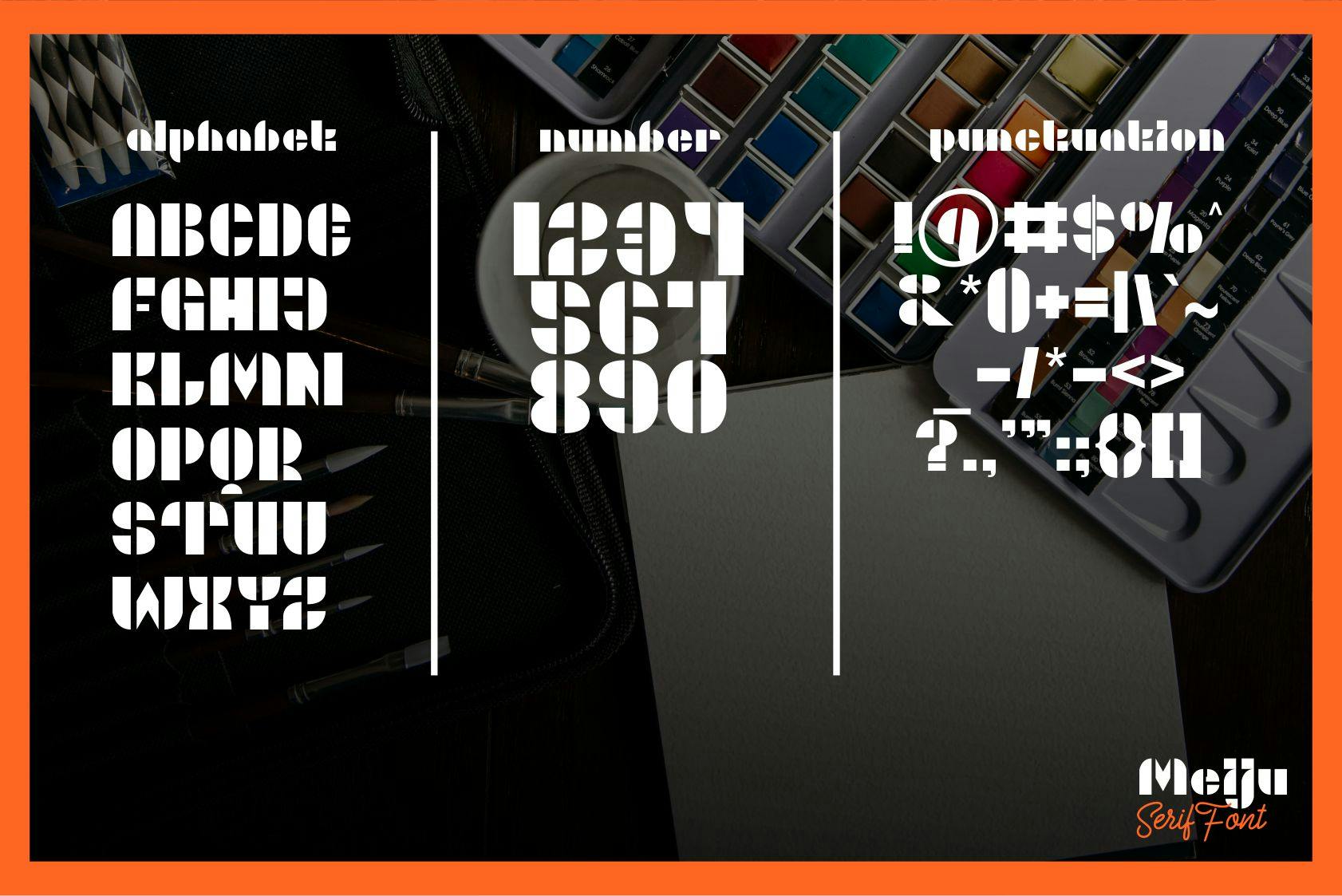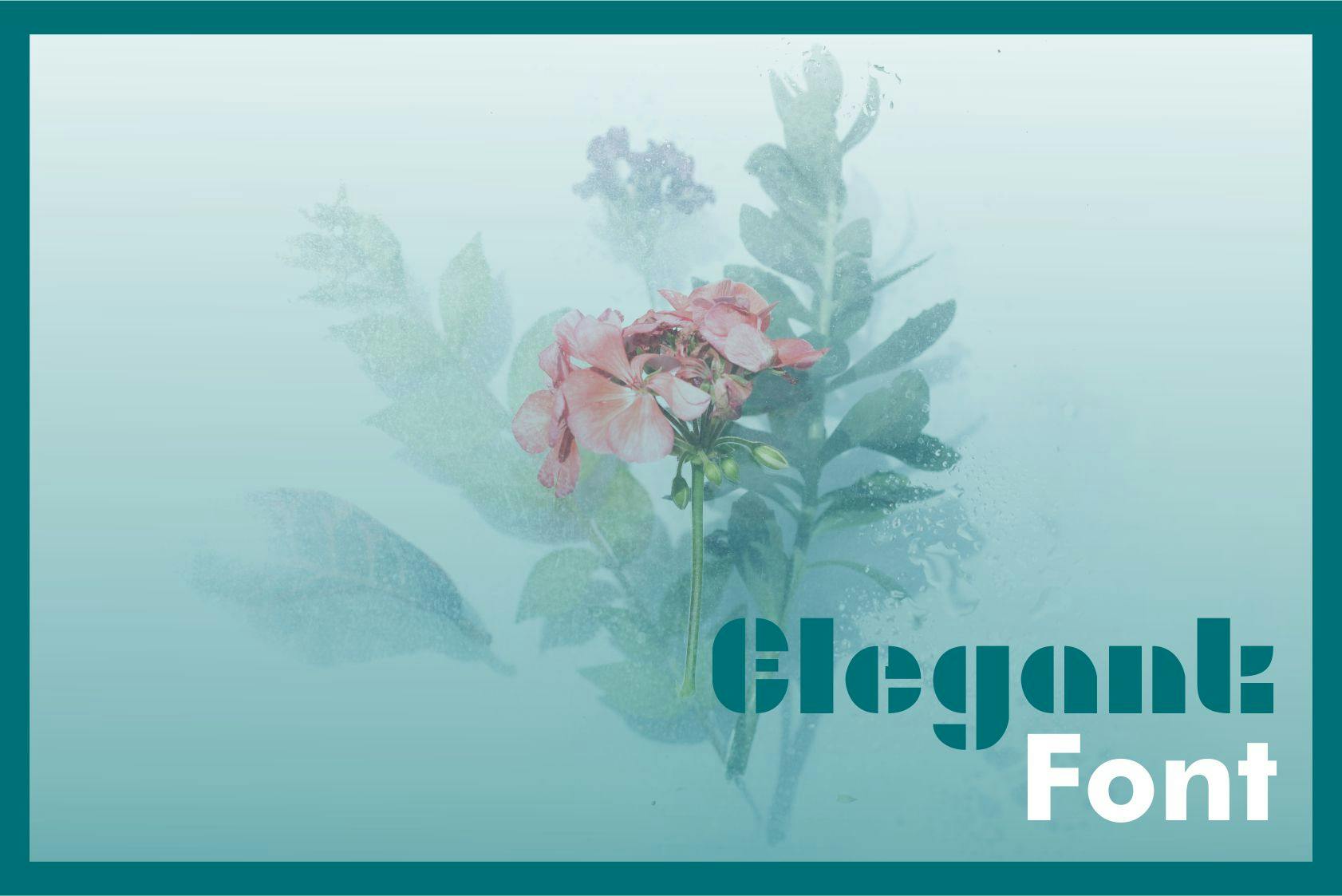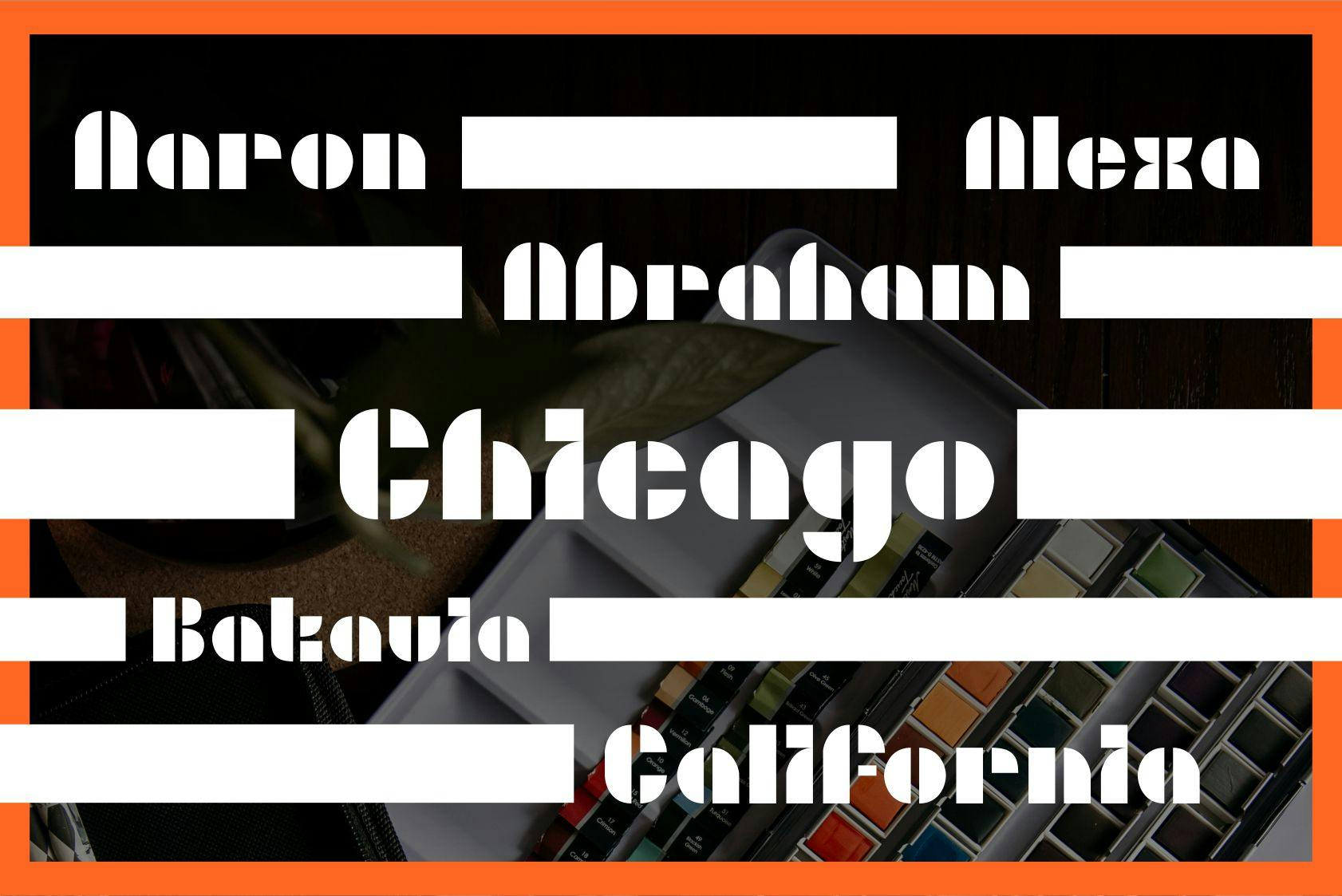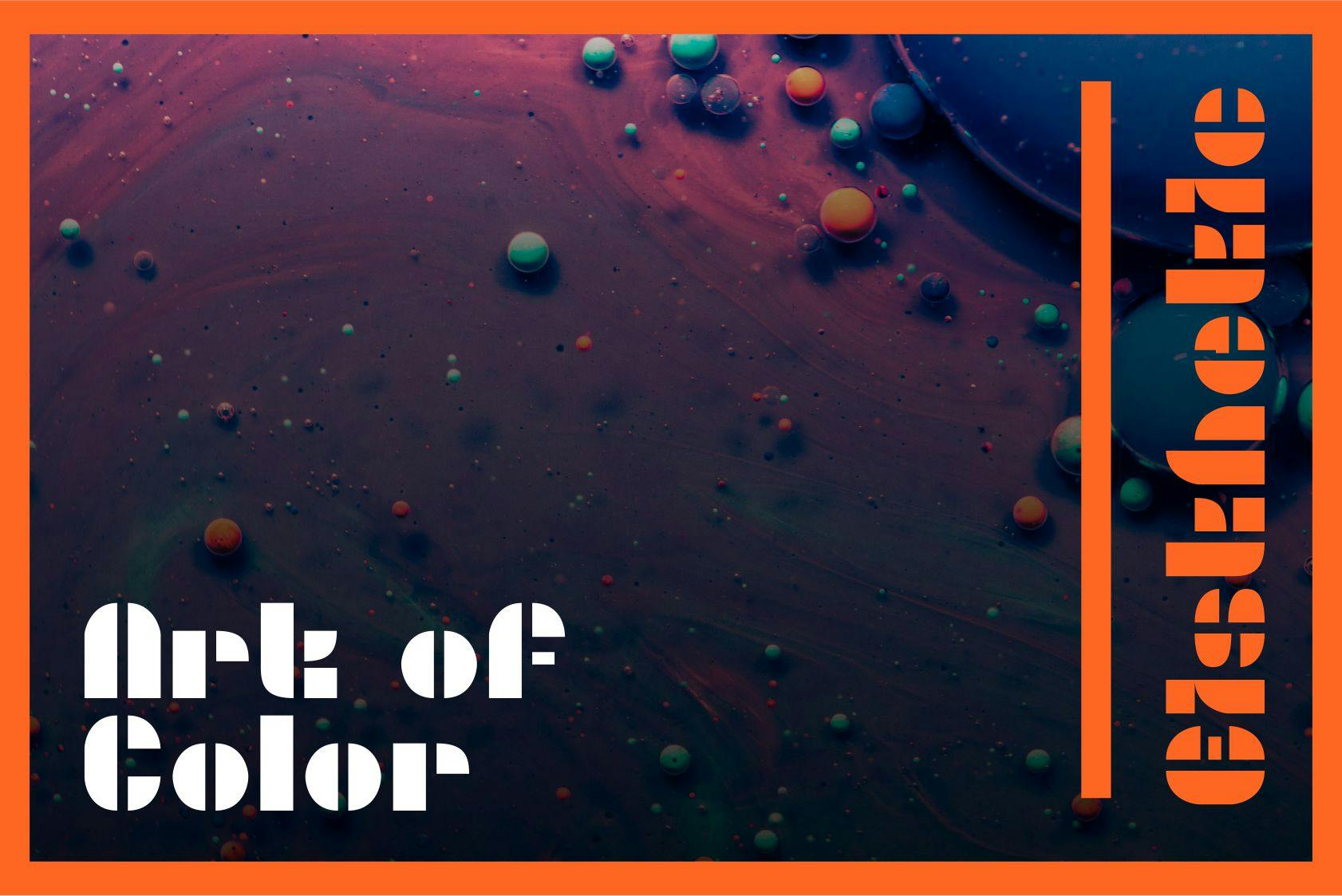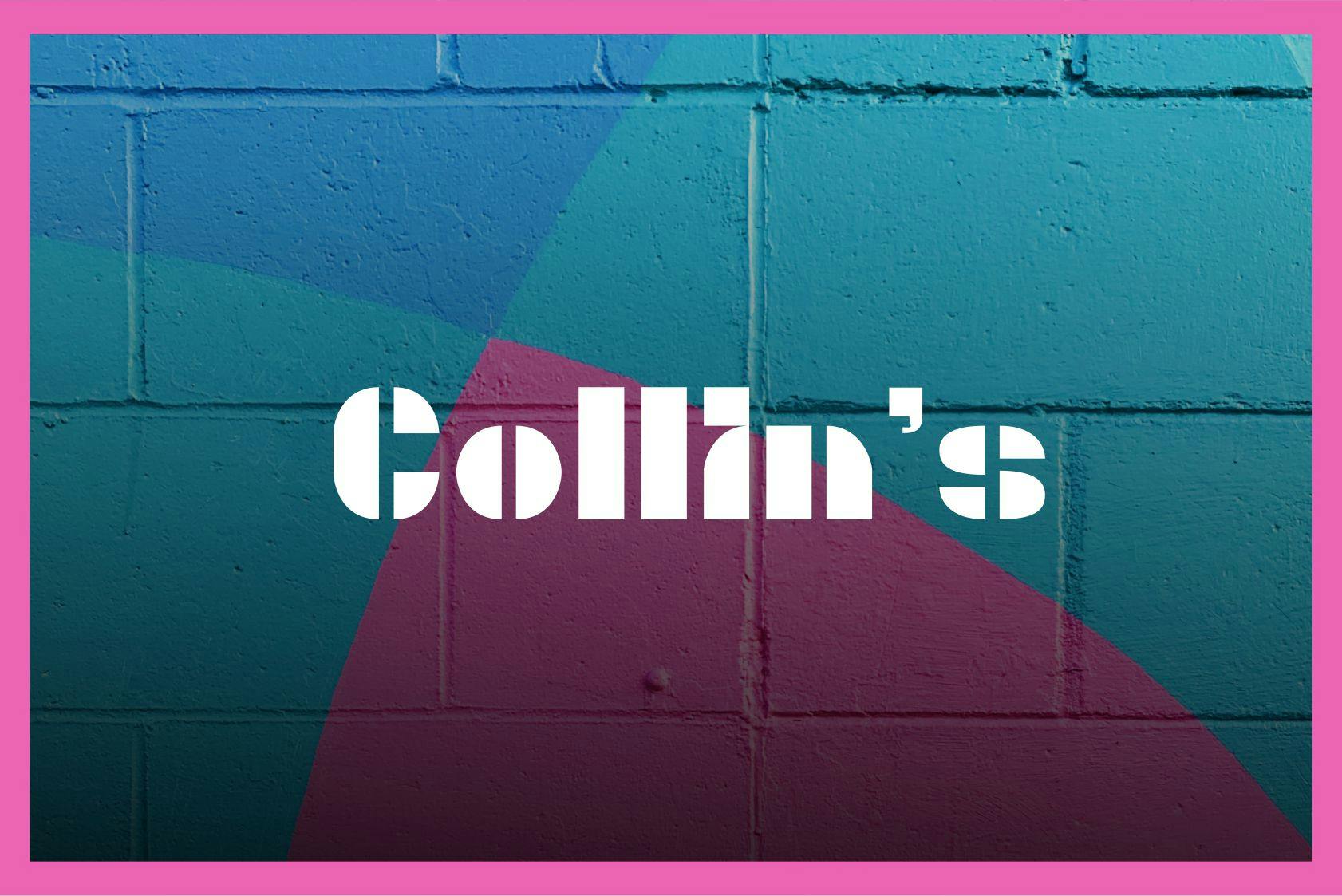
فونتهای Mijuo شامل حروف بزرگ، اعداد و دامنه وسیعی از نشانهگذاری هستند. این فونت بدون سر به سبک مدرن طراحی شده و برای پوسترها، طراحی وب، برندینگ، تصاویر، نشانها و برخی دیگر از پروژهها مناسب است.